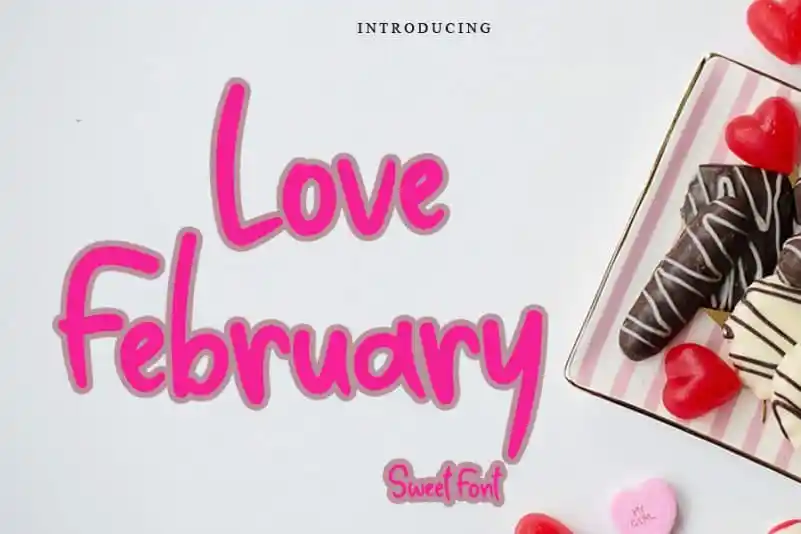
Love February Display Font – Download Grátis
A Love February Display Font é uma elegante escolha para quem deseja dar um toque alegre às suas criações digitais. Essa fonte de desenho à mão livre tem um tom encantador e desconcertantemente alegre, certamente que fará os seus projetos brilharem ainda mais. Sua personalidade leve e um pouco peculiar é perfeita para atender às demandas mais criativas da sua carreira. Quando você adiciona essa fonte à sua próxima obra, vai adorar o resultado final. Para aqueles em busca de uma mãozinha inspiradora e desconcertantemente alegre neste mês do amor, Love February é um excelente escolha.